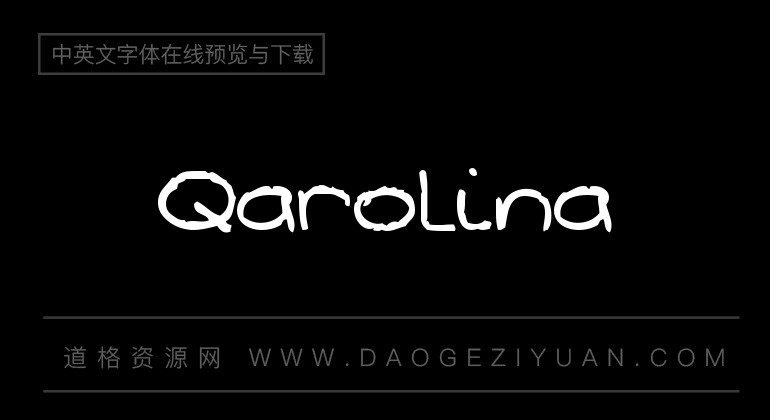
Qarolina
Qarolina 字体是一种优美、简洁的手写风格字体,由设计师Måns Grebäck于2012年创作。该字体设计灵感来源于女性的手写笔迹,因为它是由一个女性名字“Carolina”中的字母组成的。Qarolina 字体呈现出轻盈、优雅的特点,适用于各种场合的设计,例如海报、卡片、标志、招贴、包装等等。它提供了多种字重和斜体版本,能够满足不同的设计需求。 Qarolina 字体是一款付费字体,可在Måns Grebäck的官方网站上购买。
Qarolina是一款非常不错的手写艺术字体,具有很好的视觉感,适合于文化类的宣传设计、商业类品牌的广告和产品包装设计以及个性化文字排版等较多场景。